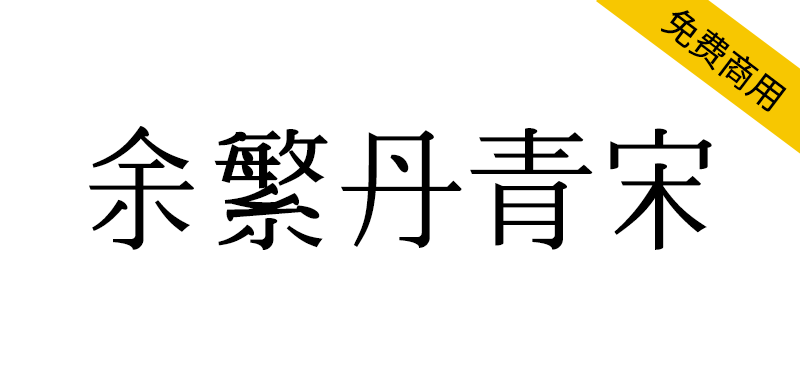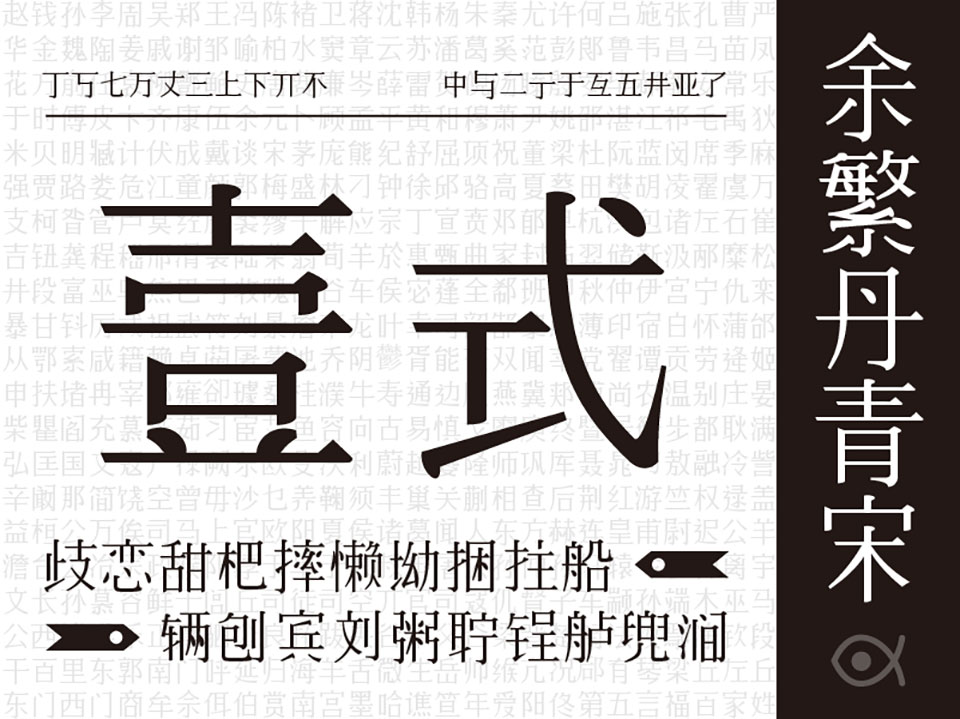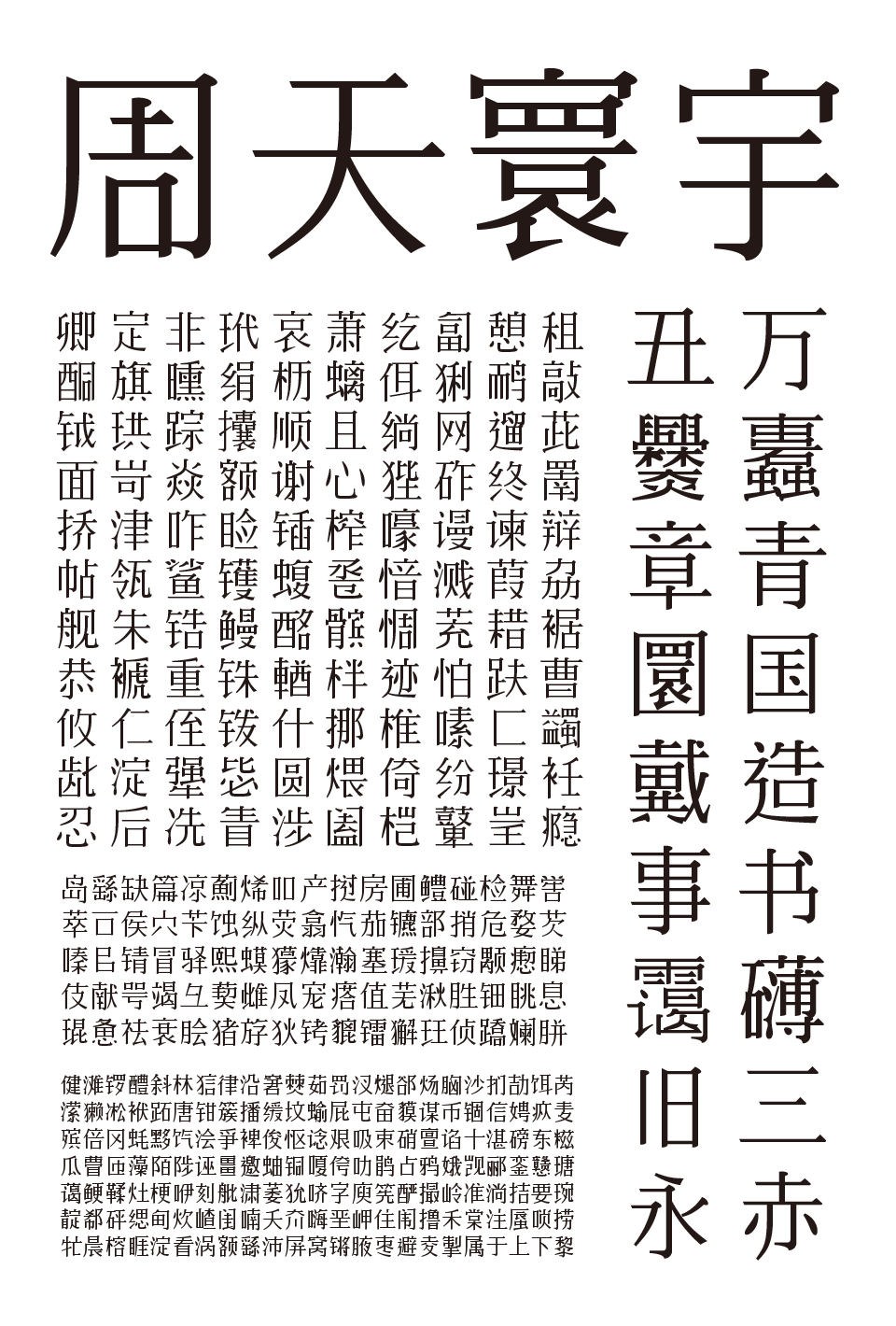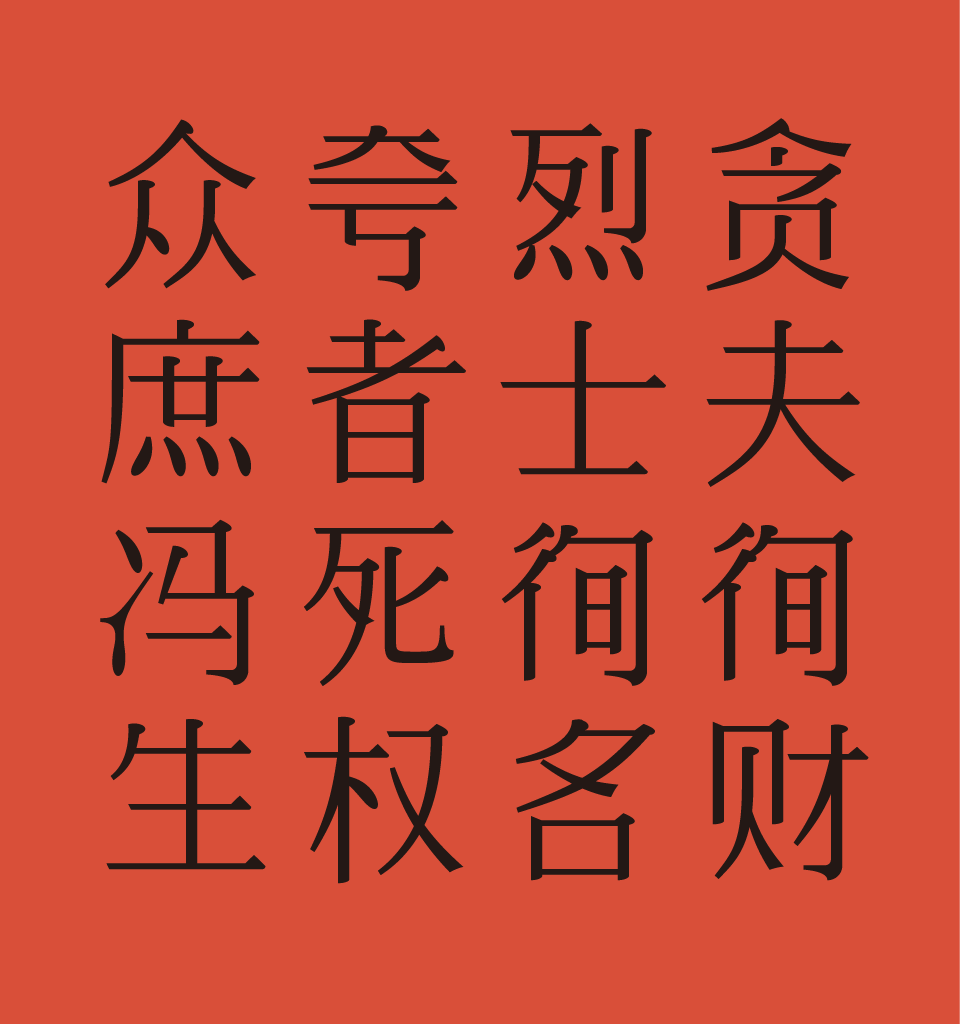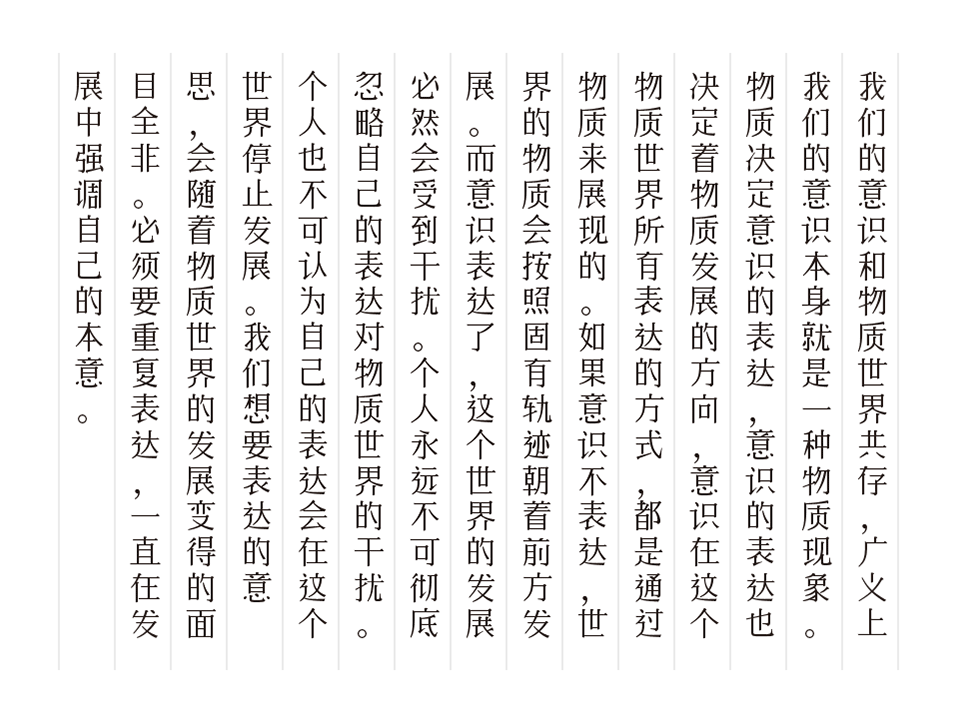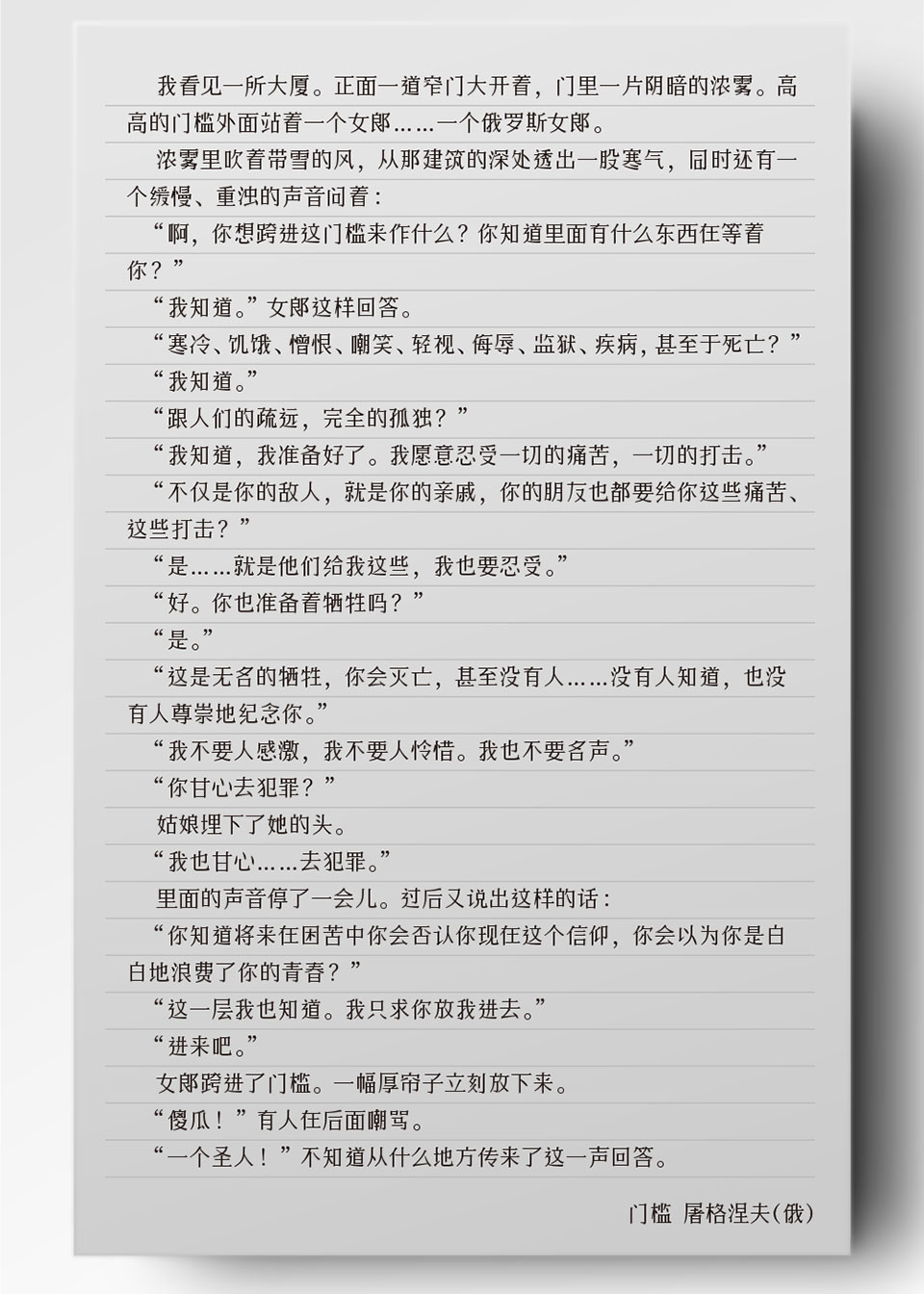
【余繁丹青宋】完全程序生成的中文字体,开源免费商用
这是一款实验字体,旨在演示完全程序生成的字体可以做到哪种程度,所以一些效果不佳之处并没有选择后期手工修正。目前看来还是过于粗糙,完全无法与手工精心制作的字体相提并论,只能算是未来可期吧。汉字骨架由动态组字系统繁星生成,西文以及标点取自思源宋体,商用也随意。